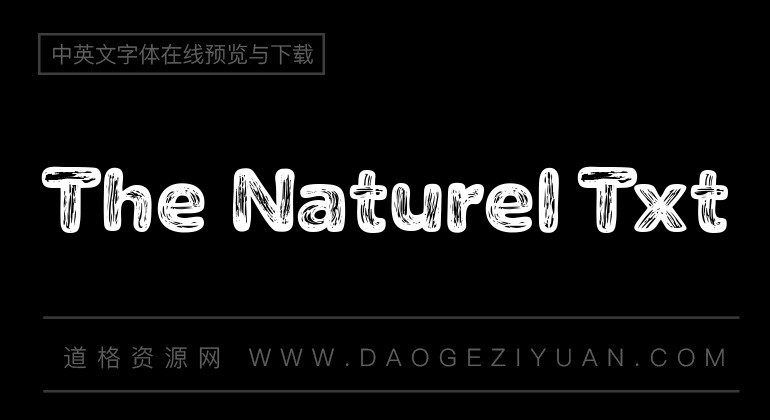
The Naturel Txt 字体是一款清新自然的文本字体,它具有非常丰富的可读性。它有大小可调的字体,可以满足不同的需求。它的字体特点是细节丰富,字形清晰,可以提供更好的可读性。它的字体也非常容易排版,可以让文字更加美观,更易于阅读。内容介绍
The Naturel Txt是一款非常不错的手写艺术字体,具有很好的视觉感,适合于文化类的宣传设计、商业类品牌的广告和产品包装设计以及个性化文字排版等较多场景。